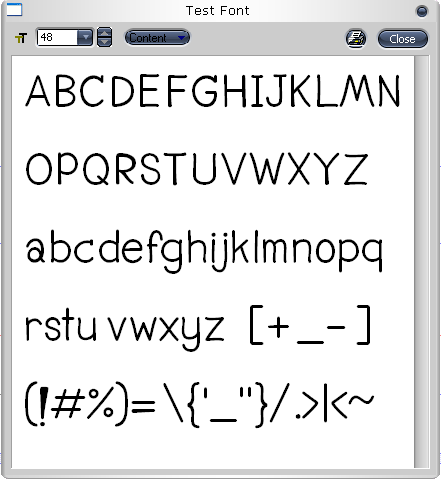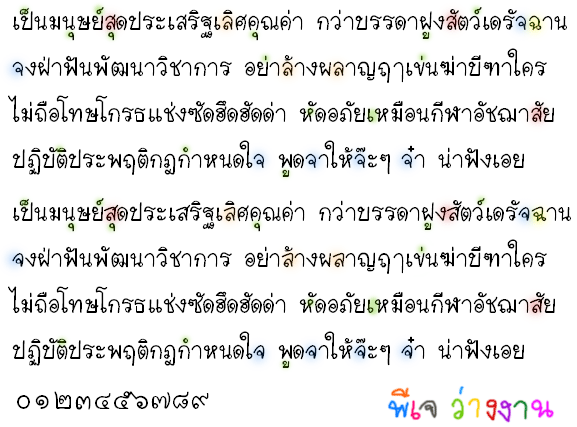
ตัวต่อไป PJ_WangNgan
สงสัยเรื่อง ฬ.จุฬา
มันมีช่อง ฬ. หางสั้น  กับฬ. หางยาว  เลยอยากรู้ว่าตัวหางสั้นมันใช้ตอนไหนคะ :09:
ตอนนี้ทำตัวหางยาวให้หางยาวเท่า ฟ.  พอเติมสระแล้วตีกันมั่วเลย :08:
อยากได้แบบหางยาว ทำยังไงให้มันใช่สระวรรณยุกต์ได้เหมือน ฟ. คะ (ต้องopentypeรึป่าว?)
อย่างคำว่า "นาฬิกา" ครับ สระอิจะไม่ได้ชนกับหาง ฬ
คิดเหมือนกัน  พอลองพิมพ์ คำว่า นาฬิกา  (ใช้เทมเพลตท่านนายพล) มันปล่อยตัวหางยาวออกมา ตีกันเลย :48:
ต้องลองใน Opentype Panel หรือไม่ก็ในโปรแกรมที่รองรับ ot ครับ จะมองเห็น
ถ้ากลัวหางทับกันก็ทำหางสั้นใส่ไว้ทั้ง 2 ตัวก็ได้ครับ แต่บาง os เขาจัดตัว ฬ ไปอยู่กับพวกหางยาวนะเวลาพิมพ์ ฬ+สระอิ มันจะหลบหางให้ อย่างบน Ubuntu
เพราะฉะนั้นอยากทำหางสั้นหางยาวก็ตามสะดวกครับ ตัวเทมเพลตก็ใส่ได้ทั้ง 2 ตัว  :01: